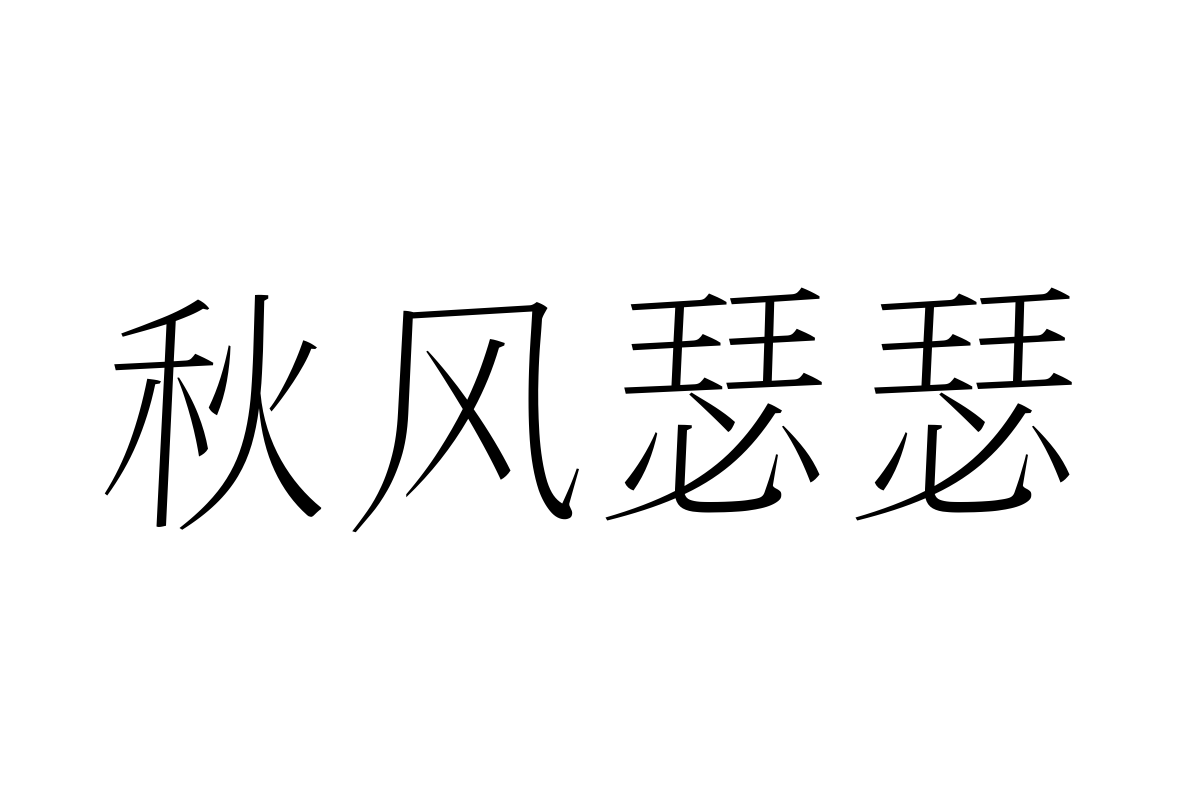
汉仪瑞意宋I 35W是一款具有现代感和科技感的中文字体,适用于各种商业、科技、教育等场合。这款字体的特点如下:
1. 字形结构:汉仪瑞意宋I 35W采用了现代简约的字形结构,笔画流畅自然,易于阅读。
2. 字重选择:该字体提供了多种字重选择,包括常规、加粗、斜体等,可以根据设计需求进行调整。
3. 字形风格:汉仪瑞意宋I 35W具有现代感和科技感,适合用于科技、电子、网络等领域的设计。
4. 适用范围:该字体适用于各种商业、科技、教育等场合,如广告、海报、网站、书籍等。